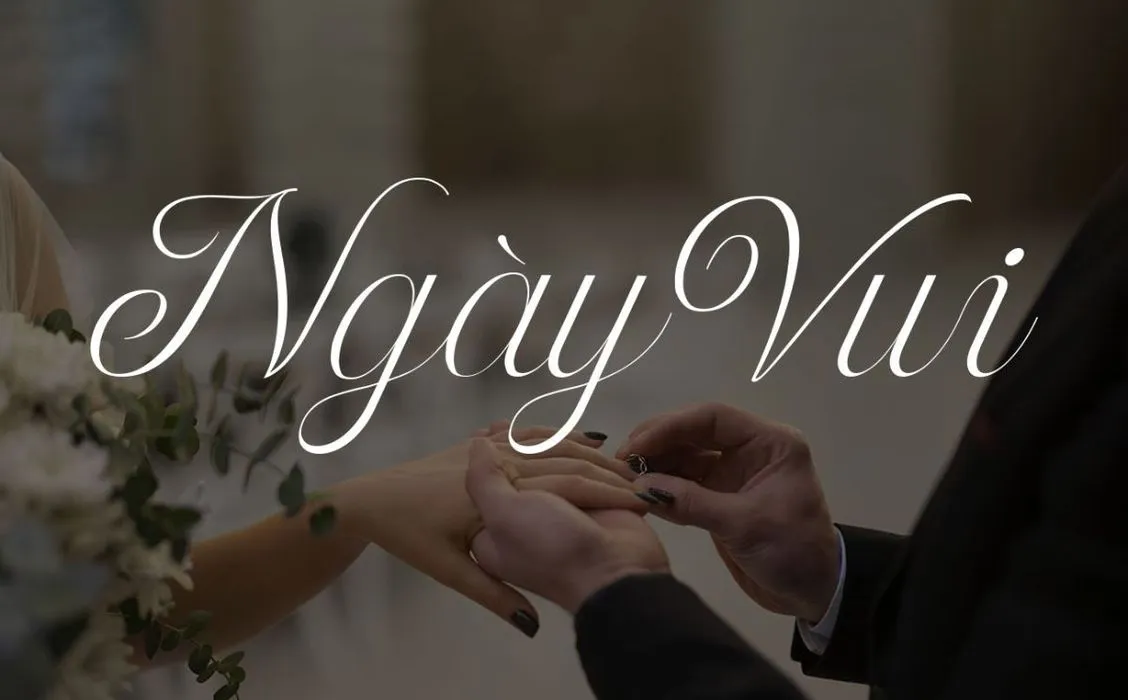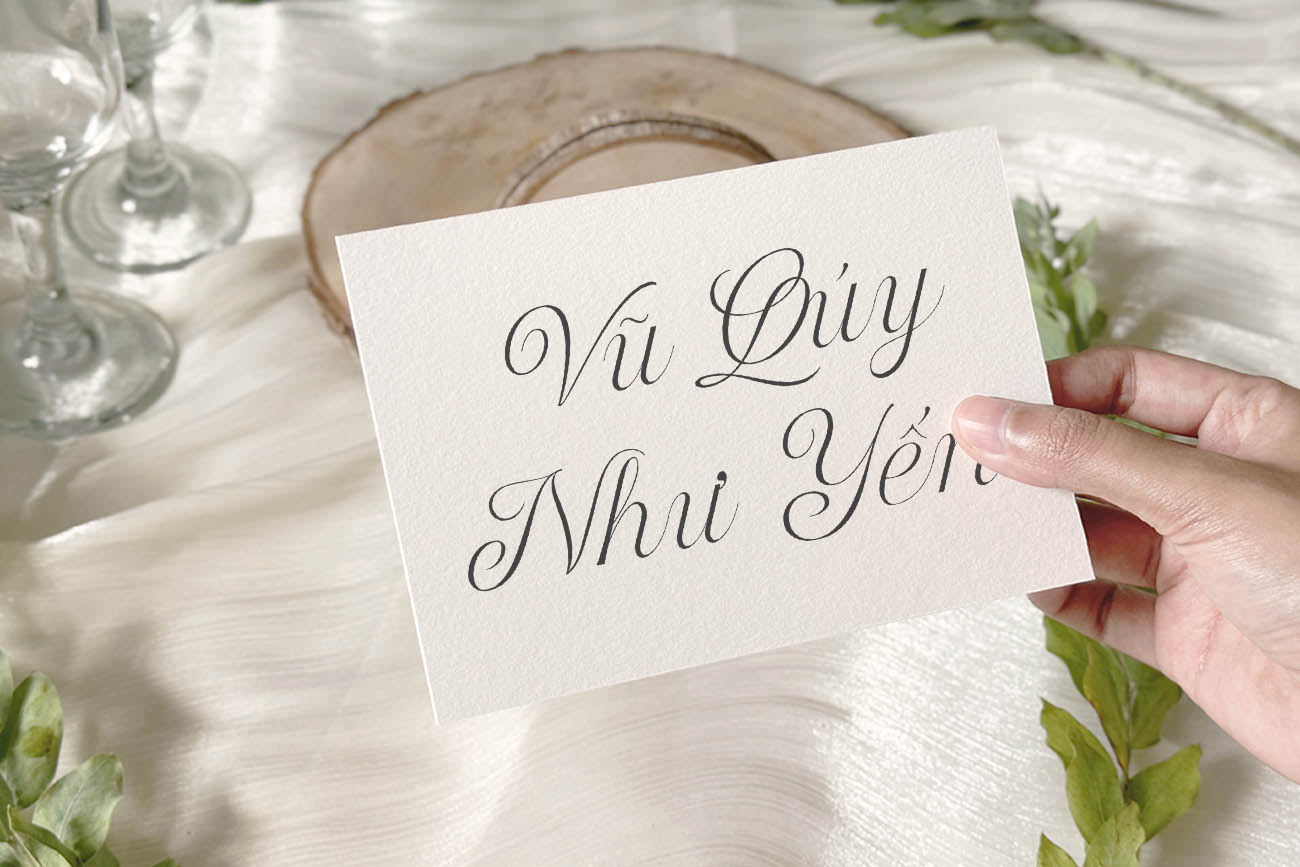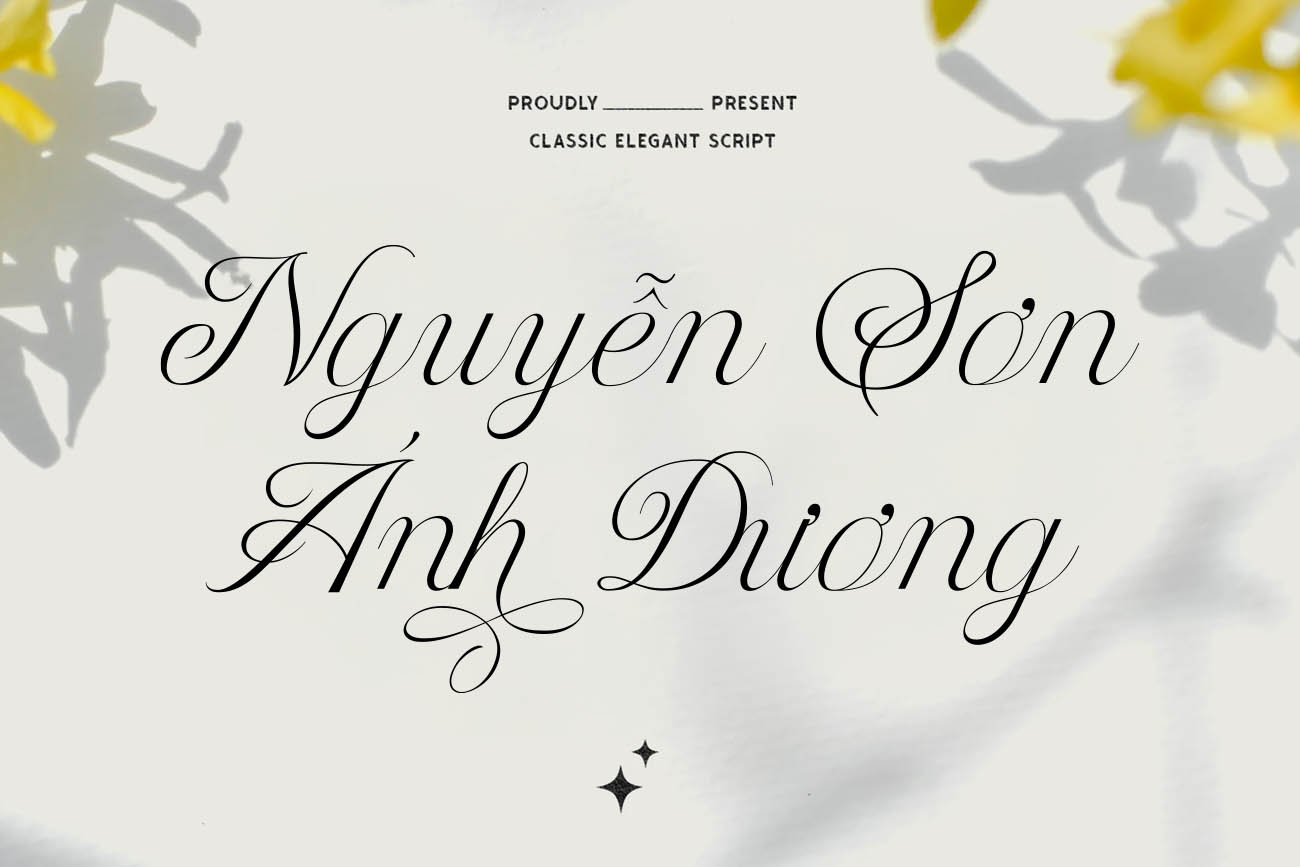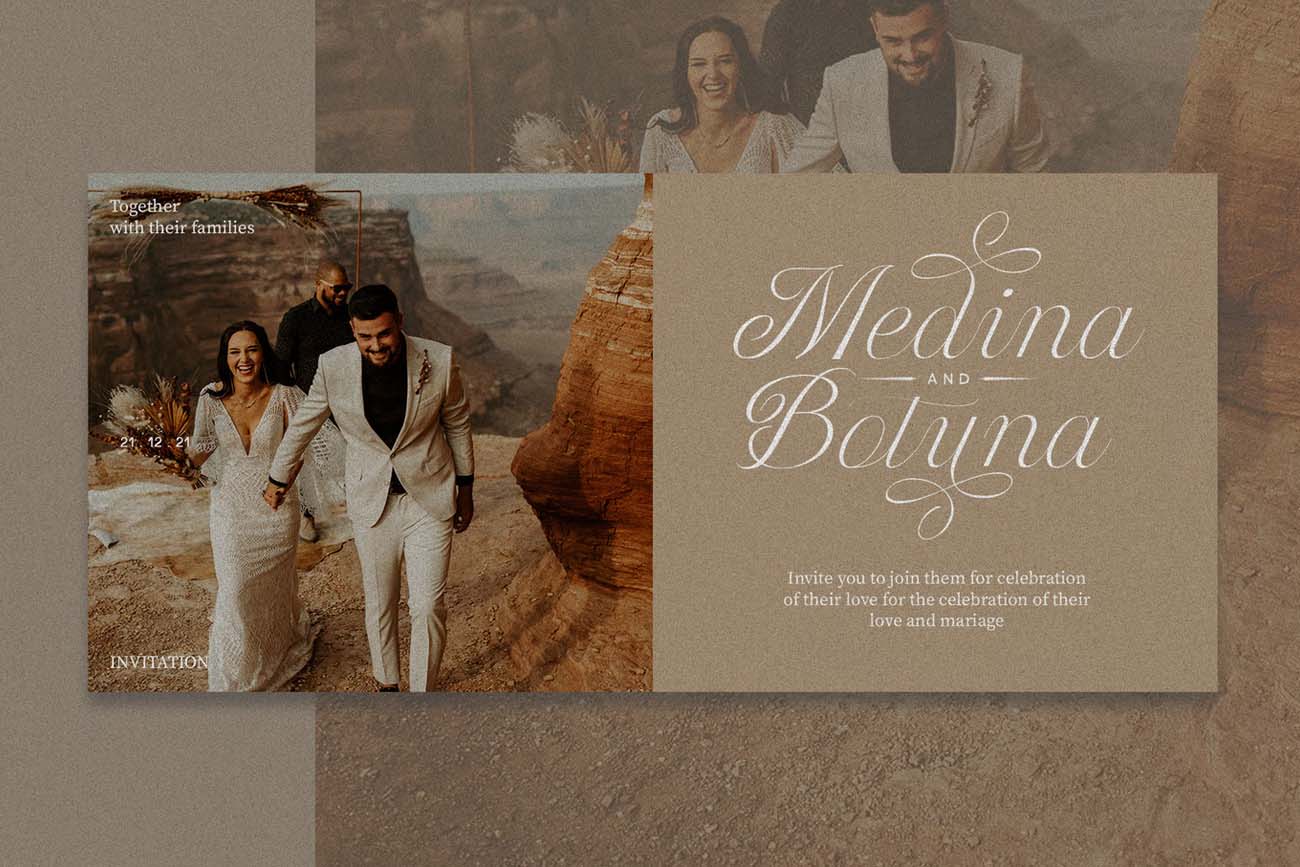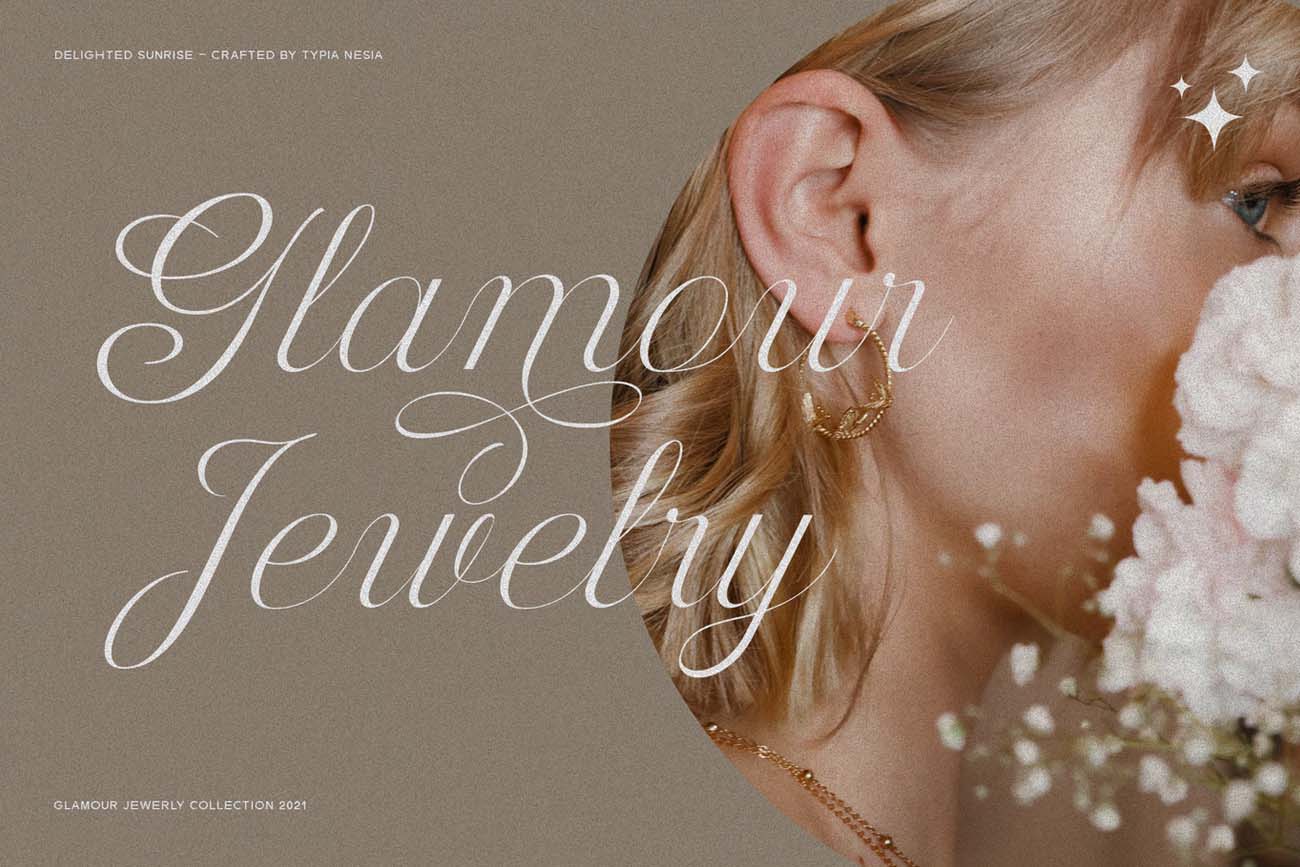
Để thổi hồn vào các dự án thiết kế tiệc cưới và sự kiện sang trọng, TH Delighted Sunrise chính là mảnh ghép hoàn hảo. Được Việt hóa trọn vẹn từ tác phẩm Calligraphy đầy cảm hứng của nhà thiết kế Yipianesia, bộ font này mang đến một làn gió mới, đầy bay bổng và chạm đến trái tim người xem.
Nghệ thuật Calligraphy đỉnh cao: Nổi bật với dáng chữ nét mảnh mang đậm chất lãng mạn. Sự uyển chuyển giữa các nét thanh, nét đậm và đường uốn lượn được chăm chút tỉ mỉ, tạo ra nhịp điệu thị giác mượt mà và tinh tế.
Font chữ cưới tiêu chuẩn: Với sự mềm mại và sang trọng bậc nhất, đây là lựa chọn hàng đầu để thiết kế thiệp cưới, vinh danh tên cô dâu chú rể, làm logo thương hiệu thời trang hay các ấn phẩm sự kiện cao cấp.
Dấu ấn Việt hóa hoàn chỉnh từ TH Team: Không chỉ đơn thuần là thêm dấu, TH Team đã tinh chỉnh để bộ dấu tiếng Việt hòa quyện tự nhiên vào các nét móc, nét hất đặc trưng. Khoảng cách (kerning) được tối ưu giúp văn bản hiển thị mượt mà mà không làm mất đi cấu trúc lãng mạn nguyên bản.
TH Delighted Sunrise là sự kết hợp tuyệt vời giữa tư duy nghệ thuật quốc tế và sự am hiểu ngôn ngữ bản địa. Hãy sở hữu ngay bộ font chữ công nghệ cưới xuất sắc này để sẵn sàng kiến tạo nên những tác phẩm thiết kế đầy cảm xúc và đẳng cấp.